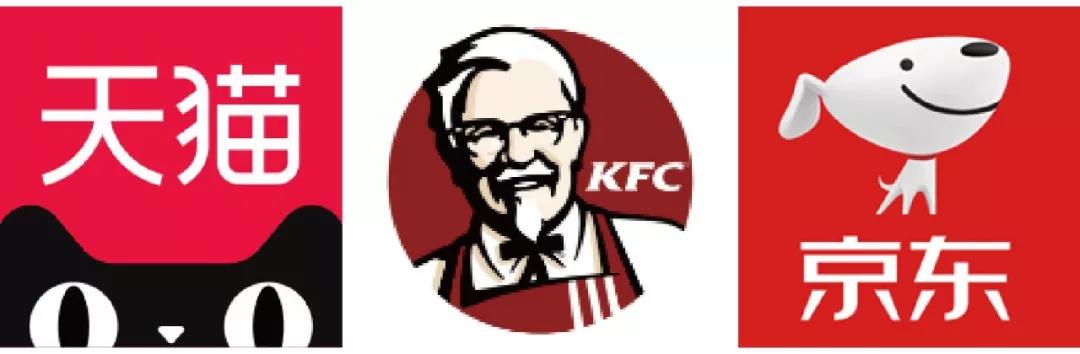
品牌标志的七种类型及运用,标志运用中有7种不同的方法
标志象征着每个企业品牌的形象,在标志运用中有7种不同的方法。
虽然它们都是排版和图像的组合,但每种标志都给你的品牌带来不同的感觉。品牌标志是目标客户首先看到的东西,所以你要确保你的标志和传达企业形象是相符正确的。
您想要为您的业务选择最好的标志类型可以通过以下7种标志:
1.字母标志
由于重点是首字母,因此您选择(或创建)的字体非常重要,以确保您的徽标不仅与您的公司的主题相符,而且在您在名片上打印时也清晰可辨。此外,如果您还不是成熟的企业,您可能需要在标志下方添加完整的商家名称,以便人们可以开始了解您的身份。
2.文字标记
此外,与字母标识一样,设计将是一个重要的过程。因为重点将放在你的名字上,所以你需要选择一个字体或者创建一个字体来捕捉你的业务的本质。例如,时尚品牌倾向于使用干净、优雅、感觉高端的字体,而法律或政府机构几乎总是坚持使用传统的、感觉安全的“较重”文字。
何时使用字母和文字标志:
如果你是一家新公司,需要把你的名字传播出去,只要确保这个名字足够短,可以充分利用这个设计就行了。任何太长的东西都会显得太杂乱。
如果你有一个独特的商业名称,并且能在顾客的脑海中留下深刻的印象,那么一个文字标志就是一个好主意。用一种设计好的字体写下你的名字会使你的品牌更加具有粘性。
字母标志和文字标志都很容易在营销和品牌之间使用,从而使它们对新业务和发展业务具有高度适应性。
请记住,当你创建字母标志或文字标志的时候,单是字体上的企业名称可能不足以捕捉到品牌的细微差别。所以,一定要选择一个专业的,有眼光的设计团队。
3.图案标志
当决定选择图形标志时,最需要考虑的是选择什么图形标志。这将会影响到你的公司的整体形象。你需要考虑你所选择的形象具备更广泛的含义:你想在你的名字上构思(就像天猫)?或者你是想创造更深层的意义(想想Snapchat幽灵标志是如何告诉我们产品的作用)?或者你想唤起一种情感(就像世界野生动物基金会一样,他们的熊猫形象,一个可爱的濒危物种)?
4.抽象标志
一个抽象标记的好处是,你能够象征性地表达你的公司所做的事情,而不依赖于特定形象的文化含义。通过颜色和形式,你可以在你的品牌周围赋予意义和培养情感。(例如:耐克是如何暗示运动感和自由感的)。
5.卡通形象标志
卡通形象标志包含插图人物的标志。卡通形象标志通常具有色彩鲜艳、通俗、直观、易于理解和记忆的特点,对标志设计品牌的“性格”塑造与推广起到了很好的效果。通常塑造出鲜活的、有个性的、受欢迎的卡通形象作为自己品牌代言人,是一种有效的标志设计类型。
卡通形象标志也可以代表公司的一个吉祥物。例如种植园主、天猫、肯德基和京东狗的卡通形象标志,对于那些希望通过吸引家庭和孩子来营造健康氛围的公司来说是非常好的。在国内互联网企业,通过卡通形象设计连接了技术与人文文化。例如阿里,就充分使用了卡通形象所带来的强大的亲和力,从而建立了自己的阿里动物园。
何时使用图案标志及符号标志:
一个图案标志可能会非常棘手,但对于一个知名品牌,也是有效的表现方式。如果公司的名字太长、或是商业名称不能很好地用于翻译,可以使用图案标志和符号标志来表达公司的业务,图形标志可以有效地用来表达公司品牌想要的传达的想法和情感。
如果公司的商业模式在未来预期有变化,一个图案标志可能不是最好的方案。例如一家餐饮公司主要销售披萨,如果在的标志中使用披萨,当这家公司开始销售三明治或汉堡时候,原本的的披萨品牌标志就无法承载更多的产品内容。
抽象标志可以为企业创建一个完全独特的形象,但抽象类型的标志设计最好交给设计专业的设计团队。在了解颜色、形状和结构如何结合起来时,能更好的设计出独特的抽象标志来诠释品牌形象。
如果想要吸引小孩子或家庭,可以考虑设计一个卡通形象的吉祥物。吉祥物的一大好处是它能与客户互动,具备社交功能。同时也是社交媒体营销以及营销活动的重要工具,例如在迪士尼小孩都非常愿意吉祥物合影留念。
吉祥物只是一个成功的标志和品牌的一部分,但吉祥物可能无法在所有的传播物料中使用它。例如,卡通形象和吉祥物不能很好地打印在名片上。所以在标志设计过程中,要考虑到标志的实际应用。
6.图形文字标志
图形和文字可以并排摆放、相互叠加或者集成在一起创建图像。一些著名的组合商标比如多力多滋、汉堡王、拉科斯特。
由于名称与图形相关联,因此组合标志是一种多功能选择,文字和图形或吉祥物组合一起都可以强化深入一个公司的品牌传达。使用图形文字标志,人们也会立刻开始将公司的名字与品牌图案标记或吉祥物相关联!将来,公司品牌可以完全依赖标志符号,而不必始终包含企业名称。
由于符号和文字的组合可以共同创建一个独特的图像,所以这些标志通常比单独的图形标志更容易商标化。
7.徽章标志
徽章标志由图形符号或图案内的字体组成,具有简练、直接、明晰、醒目的特点。徽章标志往往具有传统的外观,有着象征荣誉的重要意义,也可以表示身份和职业。因此它们通常是许多学校,组织或政府机构的首选,汽车行业也非常喜欢使用徽章标志。
虽然它们具有经典风格,但一些公司已经有效地将传统会徽外观与21世纪的标志设计进行了现代化改造,例如星美国哈佛大学校徽、巴克的标志性美人鱼、哈雷戴维森摩托。
徽章标志对细节表现的要求很高,而且名称和符号是严格地融合在一起的,因此它们的用途可能不如上述类型的标志。复杂的标志设计不容易在所有品牌中复制使用。例如在名片上使用徽章标志细节就变得很小,会变得难以阅读。如果在帽子或衬衫上绣上这种标志,那么就需要一个相对简单的徽章设计。
如何时使用图形文字标志或徽标:
一个图形文字标志是所有企业在不错的选择方式,他是多功能的,并且非常独特,是著名公司最受欢迎的标志选择。
徽章的传统外观是许多公共机构和学校的青睐,但它也能很好地在民营企业使用,特别是在食品和饮料行业:例如星巴克,啤酒标签等。但是在细节方面需要保证安全可读性。